15のベストサインフォントオプション
公開: 2022-03-23サイネージは、中小企業の成功への道を成し遂げたり、壊したりする可能性があります。 それは注目を集め、顧客を歓迎し、ブランドを意味します。 サインの内容はそれを表示するために使用されるフォントであるため、ほぼ重要です。 それは注目に値し、目に見えますか? それは適切なメッセージの感情を明確に伝えていますか? 最高のサインフォントオプションは何ですか?
サインにはどのフォントが使用されていますか?
サインにはどのフォントが使用されていますか? ディスプレイ広告にはさまざまなフォントが利用できますが、確かに他のフォントよりも一般的なフォントもあります。 プロのデザインを依頼する場合でも、DIYのビジネスサインを作成する場合でも、ほとんどの大判サインには次のフォントスタイルが適しています。
- Helvetica
- Futura
- ベバス
- プロキシマノヴァ
- アベニール
- オプティマ
- 無数
中小企業の印刷されたサインに最適なフォントを選択する方法
中小企業の印刷された看板に最適なフォントをどのように選択しますか? 一部のフォントスタイルは、ほとんどの場合、他のフォントスタイルよりも優れた看板を提供しますが、中小企業の所有者は、看板をデザインする際に何千ものオプションを利用できます。 幸い、次の要因を考慮することで、範囲を大幅に狭めることができます。
フォントカテゴリを理解する
選択できるフォントは数千ありますが、ほとんどすべてがいくつかの一般的なカテゴリに分類され、一部は他のフォントよりも看板やディスプレイ広告に適しています。 セリフ、サンセリフフォント、スクリプト、ノベルティフォントのスタイルの違いを理解すると、独自のディスプレイのレタリングを選択するのに役立ちます。 サンセリフフォントは、遠くから見たときに文字がくっきりと鮮明なままであるため、一般的に大きな看板に適しています。
ブランドガイドラインを忘れないでください
サイン、ポスター、その他のディスプレイ広告を作成するときは、ブランドのスタイルガイドラインを順守することが重要です。 結局のところ、ブランドは企業が顧客の心の中でどのように表現されるかであり、異なるスタイルの看板をデザインすることは、ディスプレイのマーケティング目的を損なうことになります。 ブランドのロゴとスタイルに一致するフォントを選択できない場合は、少なくとも同じまたは無料のフォントファミリから1つを選択してみてください。
サインの使用を検討する
サインはどのように使用されますか? 中小企業の所有者は、遠くから見るために選択するのとは異なるフォントを綿密な検査のために選択します。 また、一部のコミュニティやエリアには、特定の場所に表示できるフォントの種類とテキストのサイズに関する特定の要件があるため、標識が表示される場所も検討してください。 ワールドワイドウェブコンソーシアムは、ウェブサイトで看板を表現することを計画している場合、大規模なテキストのコントラスト比も提案していることを忘れないでください。
キャピタライゼーションの使用に焦点を当てる
一部のフォントスタイルは、従来の文またはタイトルの大文字化で使用するとより強力になりますが、他のフォントスタイルはすべて大文字で表示するとより効果的に機能します。 したがって、標識に最適なフォントを選択するときは、必要な大文字の使用法を考慮することが重要です。 短いメッセージのある大きな屋外の看板は、大文字で表記するのが最適ですが、テキストの多い看板や小さい形式で表示される看板は、タイトルや文の大文字で表示すると、一般的に読みやすくなります。
最高のサインフォントオプション
何千もの利用可能なフォントスタイルが利用可能ですが、標識に最適なフォントをどのように選択しますか? ディスプレイのレタリングを選択するときは、完璧なフォントオプションをどこで選びますか? 次のフォントの例を含め、あらゆる記号に最適な多数のフォントを備えたAdobeやEnvatoElementsなどの最高のフォントサイトを利用することをお勧めします。
1.錬金術師セリフフォント
EnvatoElementsやその他のソースからの優れたフォントであるAlchemistSerifは、クラシックなTimes New Romanに似た要素を備えており、明確で独特なデザインになっています。 セリフフォントは、任意のサイズとさまざまな間隔オプションで利用できます。
2.エトナサンセリフフォント
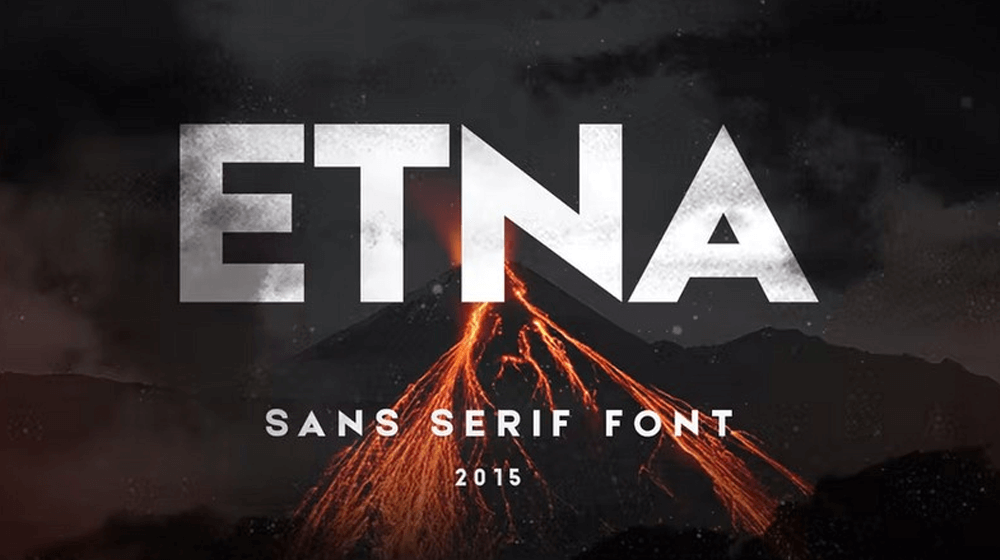
Envato Elementsは、この視覚的に心地よいフォントを提供する1つのソースであり、あらゆる標識で注目を集めることができます。 Etna sans serifフォントは、大きな看板やディスプレイで最高の精度と美しさを実現するように設計されたカスタム書体です。
3.レイドランド–ブラッシュスクリプトフォント
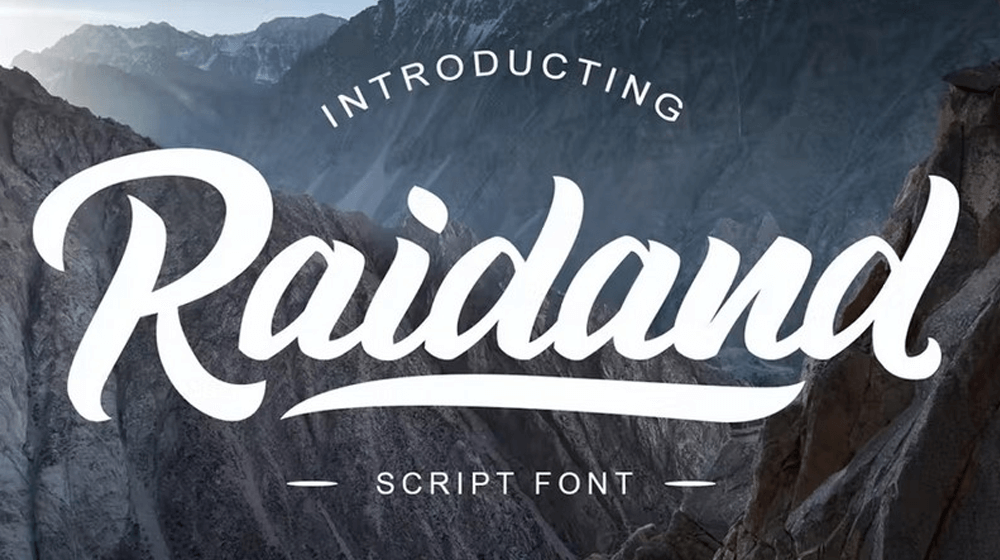
スクリプトフォントは通常、標識に最適なフォントにはなりませんが、EnvatoElementsやその他のソースからのRaidlandブラシスクリプトフォントはその規則の例外です。 フォントのすっきりとしたスタイルは、ロゴやポスターに役立ち、遠くからでも読みやすくなっています。
4.リクエスト–フォントの表示
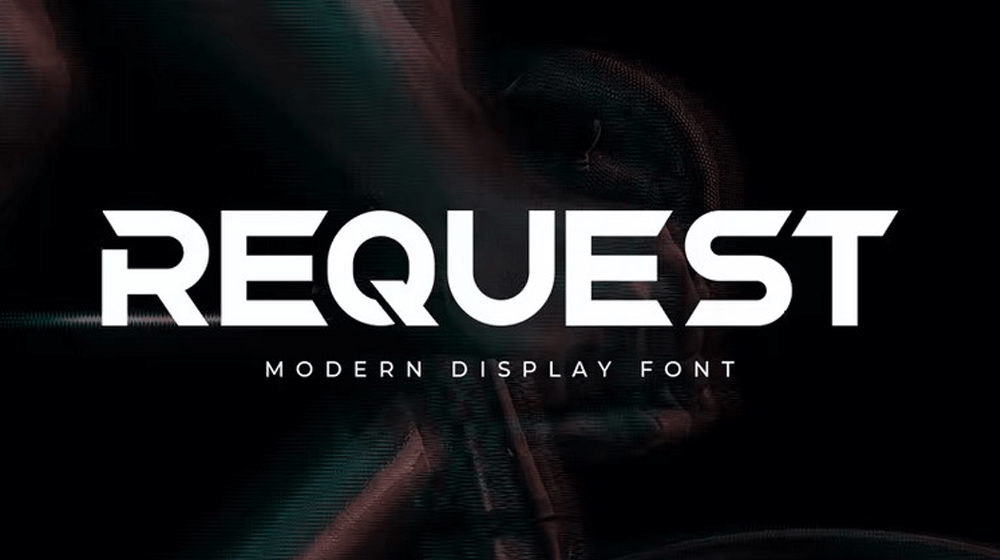
Envato Elementsは、大きな看板に明確なメッセージを提供するために大胆なステートメントを作成するRequestdisplayフォントを備えたソースの1つです。 サンセリフフォントは、抽象的な要素を使用して、さまざまな形式で目立ち、注目を集めます。
5.タホフォント
Envato Elementsやその他のソースからのもう1つのユニークな表示フォントであるタホフォントは、ロゴ、見出し、大きな看板などの大きなテキストに最適なサンセリフ文字を備えています。 さまざまな間隔オプションで利用できるこのフォントは、Webだけでなく、大規模なプレゼンテーションにも最適です。
6.FuturaPTフォント
アドビは、人気のあるFutura PTフォントを含む、大判サインに最適なあらゆる種類のフォントを備えています。 幾何学的なサンセリフ書体は、ほぼ1世紀にわたって使用されており、その明快さと読みやすさから、標識の一般的な選択肢となっています。